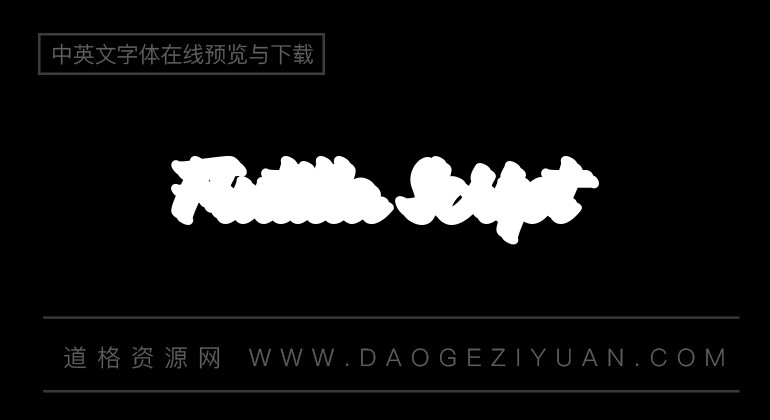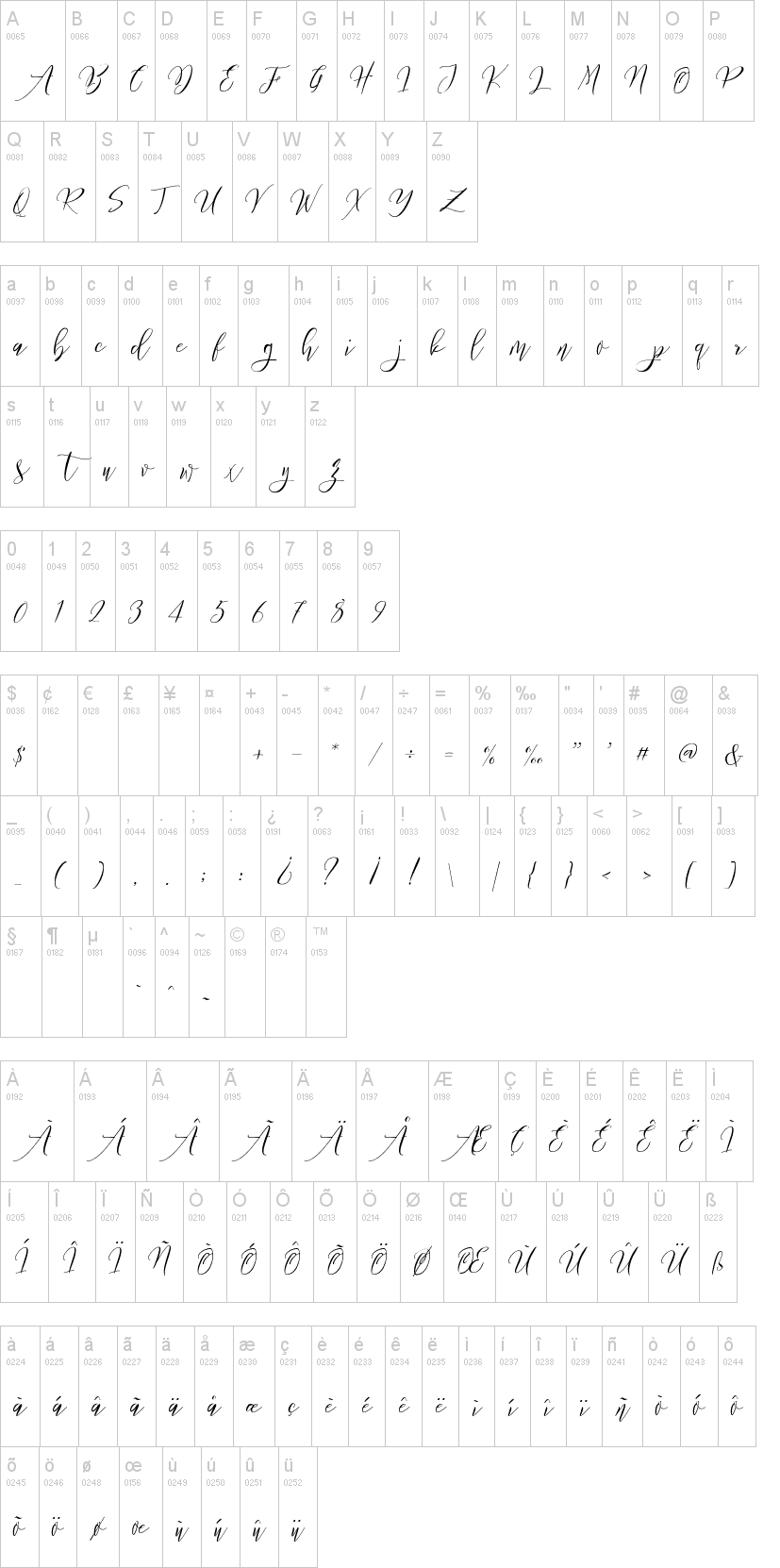
Frutilla Script
Frutilla Script 是一款华丽而柔美的手写脚本字体。它具有温暖的笔画,演绎出诗意的文字景象,让文字绽放出生动的色彩,具有极强的视觉冲击力。它既可以用于商业设计,也可以用于社交媒体、海报、海报、书籍封面、T恤设计等多种场景。它还可以作为卡通字体使用,可以营造出活泼可爱的氛围。
Frutilla Script是一款非常不错的手写艺术字体,具有很好的视觉感,适合于文化类的宣传设计、商业类品牌的广告和产品包装设计以及个性化文字排版等较多场景。
Frutilla Script字符映射图